上首造字,专注字体设计与开发十一年。致力打造企业品牌的视觉优势,进而提升品牌形象;努力让汉字更具魅力,为中小企业和设计师提供更多优质字体。我们团队钟爱字体,创始至今一直专注汉字的设计应用与研发。我们设计团队平均从事商业设计5-10年,对商用字体设计有独到的见解,擅于观察当下字体流行趋势,进而设计出既美观又实用的字体。
上首造字: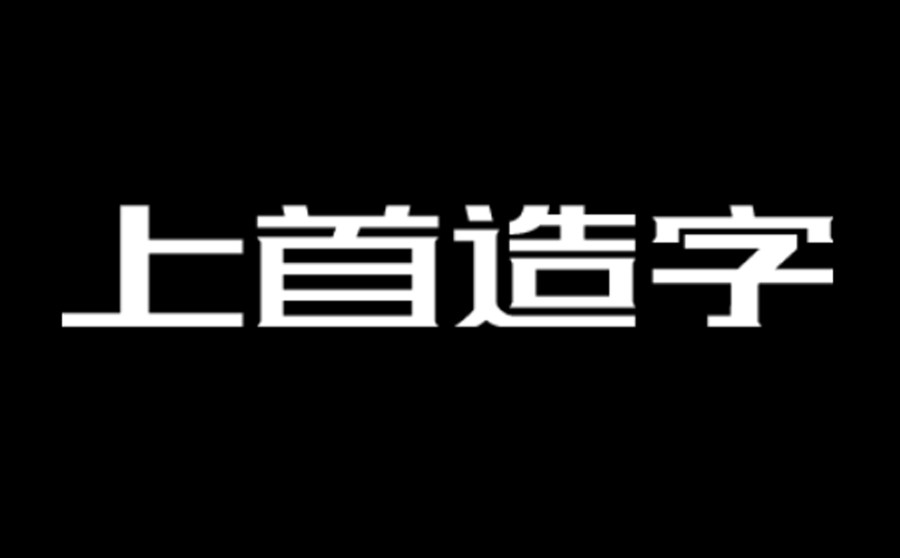
上首造字,专注品牌字体设计与开发八年。致力为中小企业和设计师提供更多优质字体,为品牌视觉系统打造优势。我们团队钟爱字体,创始至今一直专注汉字的设计应用与研发。我们设计团队平均从事商业设计5-10年,面对年轻化的消费主力军,字体整体风格偏向于年轻化。
目前汉字字体设计事业发展繁荣,新颖优秀的汉字字体层出不穷,用户审美也逐步提升,需求也越来难满足,这促使我们更加努力。
上首已发布字体系列:
上首锐博体、上首方圆、上首时尚、上首维黑、上首秀黑